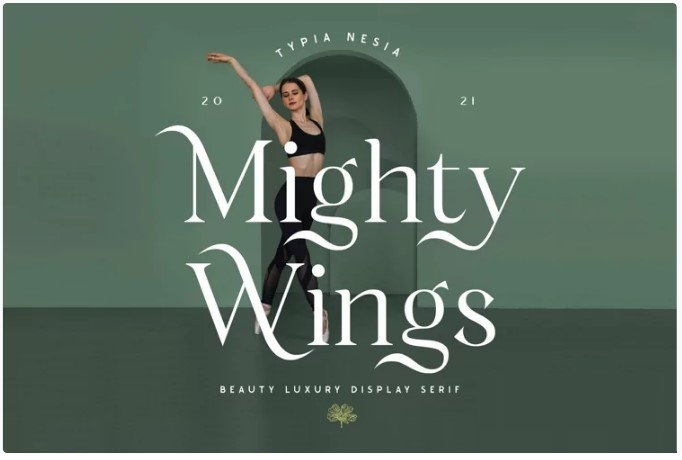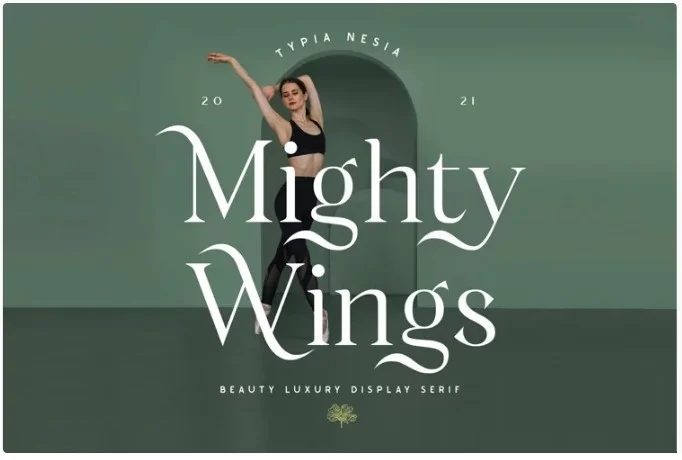
Название: Mighty Wings Font (2021)
Mighty Wings - Elegant Classy Display Serif - женственная красота роскошный шрифт!
Шрифт Mighty Wings включает в себя несколько альтернатив и лигатур. Вы можете комбинировать их, чтобы создать идеальный шрифтовой дизайн. Он идеально подходит для ваших будущих проектов. Например, роскошный логотип и брендинг, стильный редакционный дизайн, женский журнал, косметический бренд, модный промоушен, брендинг художественной галереи, музея, исторических архитектурных сооружений, брендинг бутика, дизайн канцелярских принадлежностей, дизайн блога, современный рекламный дизайн, пригласительная открытка, художественная цитата, домашний декор, название книги/обложки, специальные мероприятия и многое другое.